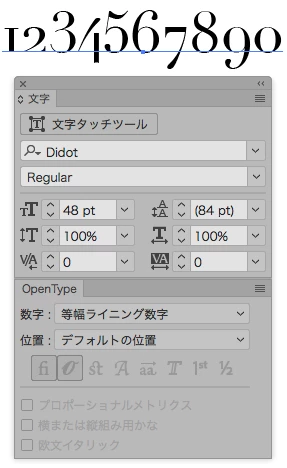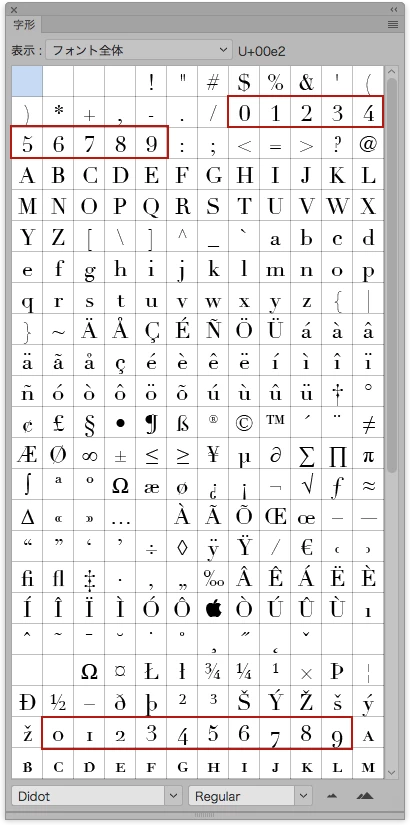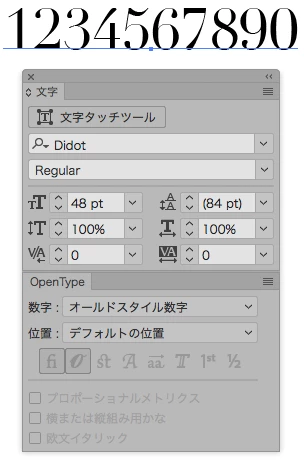
Illustratorで表示されるフォントが、fontbookで表示されるフォントと異なります。
Illustratorで表示されるフォントが、font bookアプリで表示されるフォントと異なります。
再起動や、キャッシュのクリア、フォントのアンインストール&再インストールを行いましたが改善されません。
対象フォント: Didot レギュラー 数字のみ異なってしまいます。
AppleのDidot.ttc バージョン9.0d2e1じゃないですか。フォントのバグだと思います。
Didot Regular 数字:等幅ライニング数字
Didot Regular 数字:オールドスタイル数字
両方ともオールドスタイル数字で切り替わりません。
Adobe OpenType FontのArno Proの場合は
Arno Pro Reglar 数字:等幅ライニング数字
Arno Pro Reglar 数字:オールドスタイル数字
Arno Pro Reglarではこのように切り替わります。
数字を1文字づつ選択して字形パレットで切り替えればFontBookと同じ等幅ライニング数字に出来ますが、面倒でとてもやってられません。
OS X 10.8 以前の Didot.ttc バージョン 6.1d4e1 を使うと等幅ライニング数字に固定されます。
長い時間悩まされていたので、字形パレットで発見できた時は感動しました!
ひとまず、一文字づつ文字パレットで切り替え&コピペで対応しようと思います。
確認なんですが、Didotって、OS標準付属のフォントではないのでしょうか。
Appleの出しているリストの中にはそれが含まれています。
あわせて、実際にどのような状態で違いが出ているのかを、
スクリーンショットで明示されたほうがいいかもしれません。
(FontBookとIllustrator上での数字の状態や、Illustratorでの文字パネルでのフォント名など)
まさにsilk-m さんがスクショして下さっている現象そのものです!